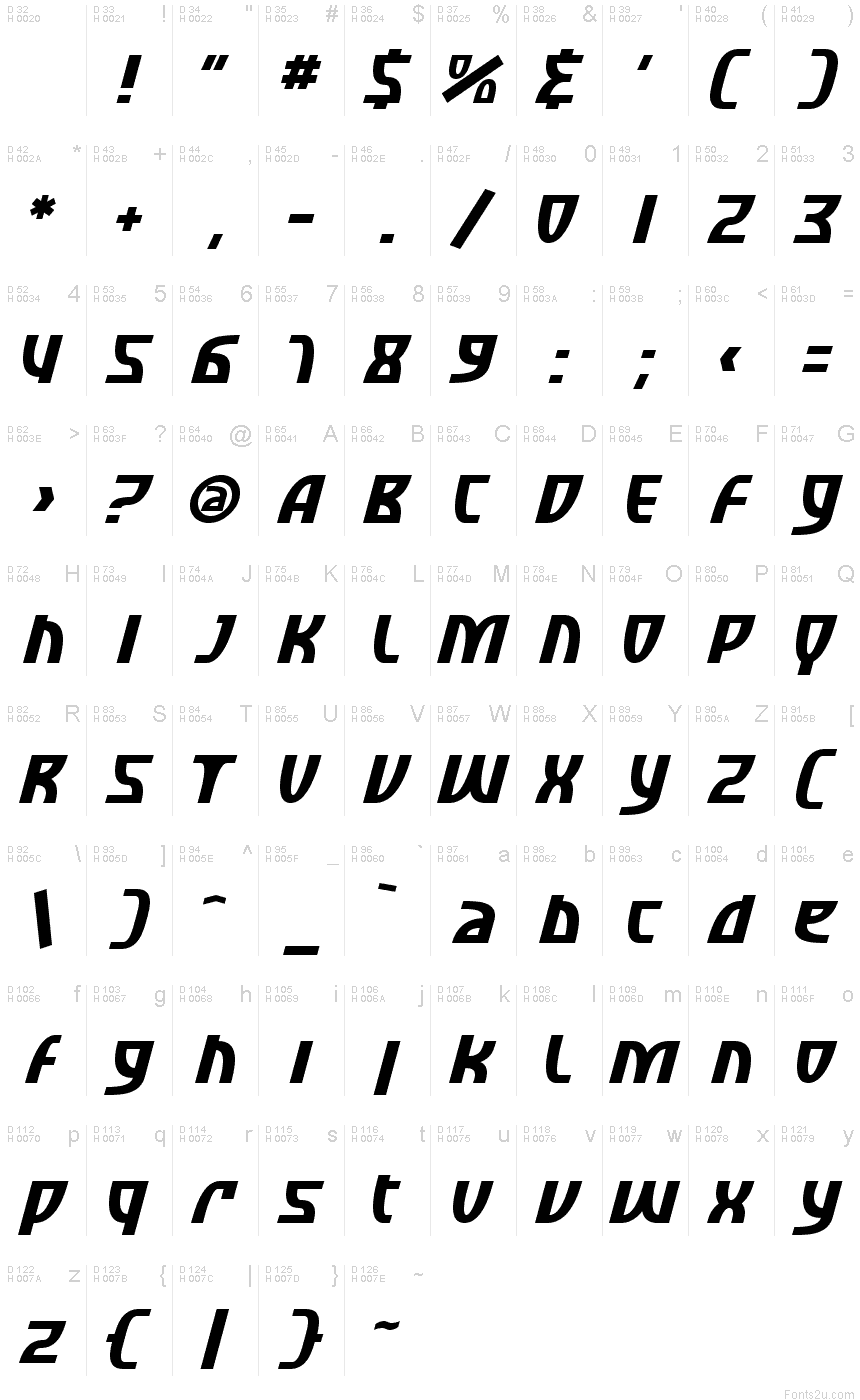
SF Retroesque Italic von ShyFonts Type Foundry ist eine kostenlose Retro-Display-Schrift mit einer rasanten Neigung, die an das späte 20. Jahrhundert erinnert. Die Buchstaben wirken, als wären sie aus kräftigen, schwarzen Formen geschnitten; eine Mischung aus abgerundeten Ecken und scharfen, kantigen Verbindungen verleiht dem Alphabet einen stromlinienförmigen Rhythmus, der perfekt für die Werbung geeignet ist.
Sie passt hervorragend in Plakatüberschriften, auf Albumcover, für Logoskizzen, von Arcade-Spielen inspirierte Verpackungen und Zeitschriften-Titel, wenn eine kostenlose Schrift einen Retro-Vibe braucht, ohne kitschig zu wirken. Da die Formen stark nach vorne neigen und ihre Kurven kompakt bleiben, eignet sie sich auch ideal für kurze Titelkarten und prägnante Wortmarken, die einen synthetischen Look im Stile der Chrom-Ära vermitteln wollen.